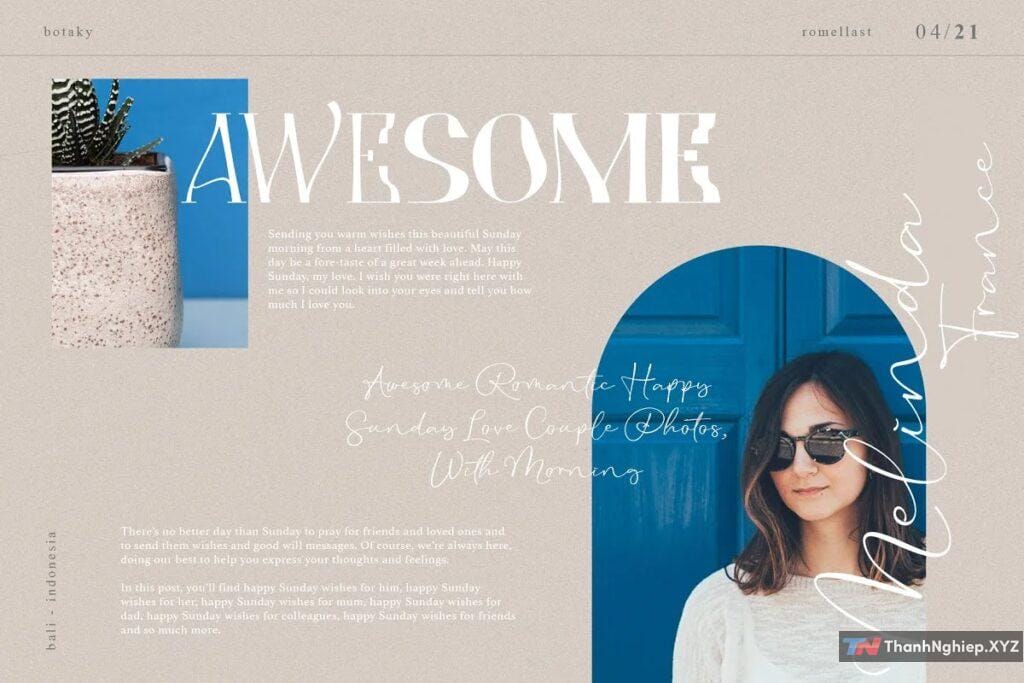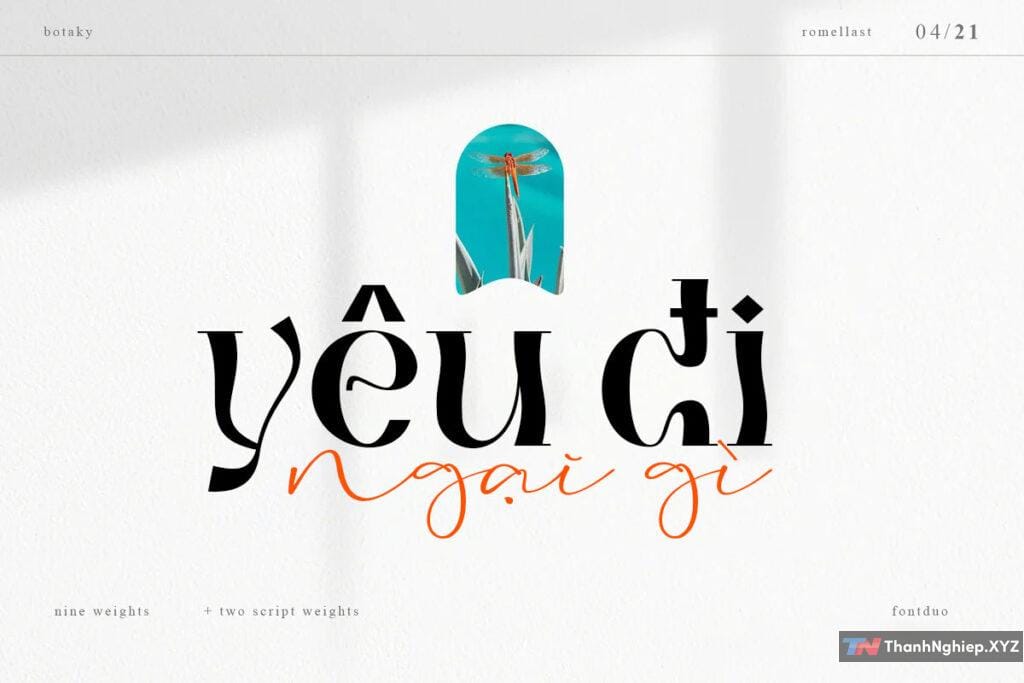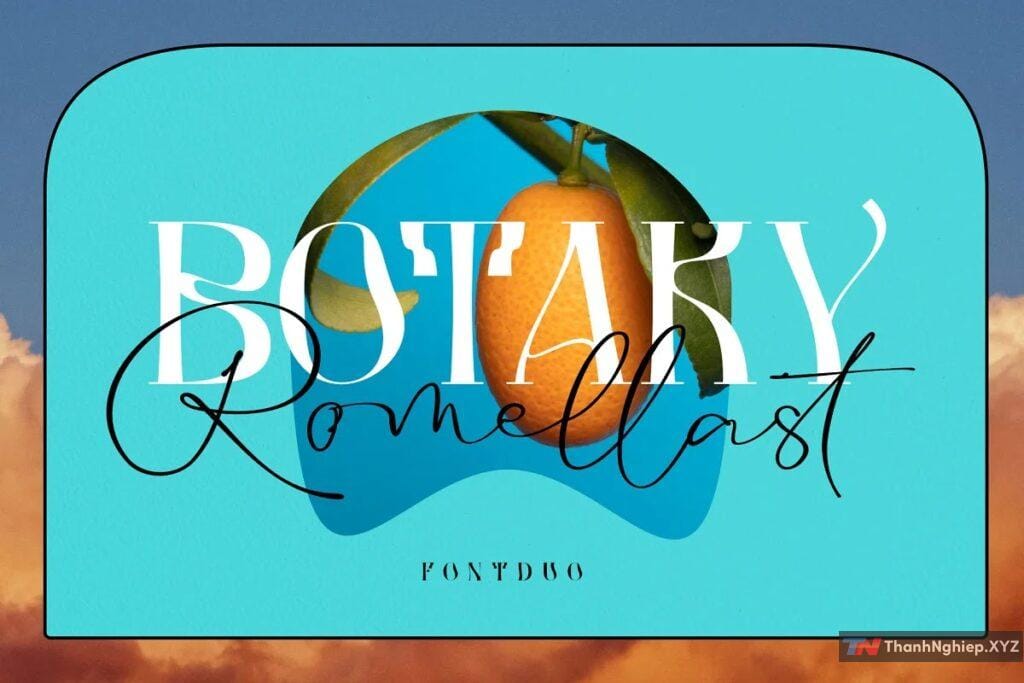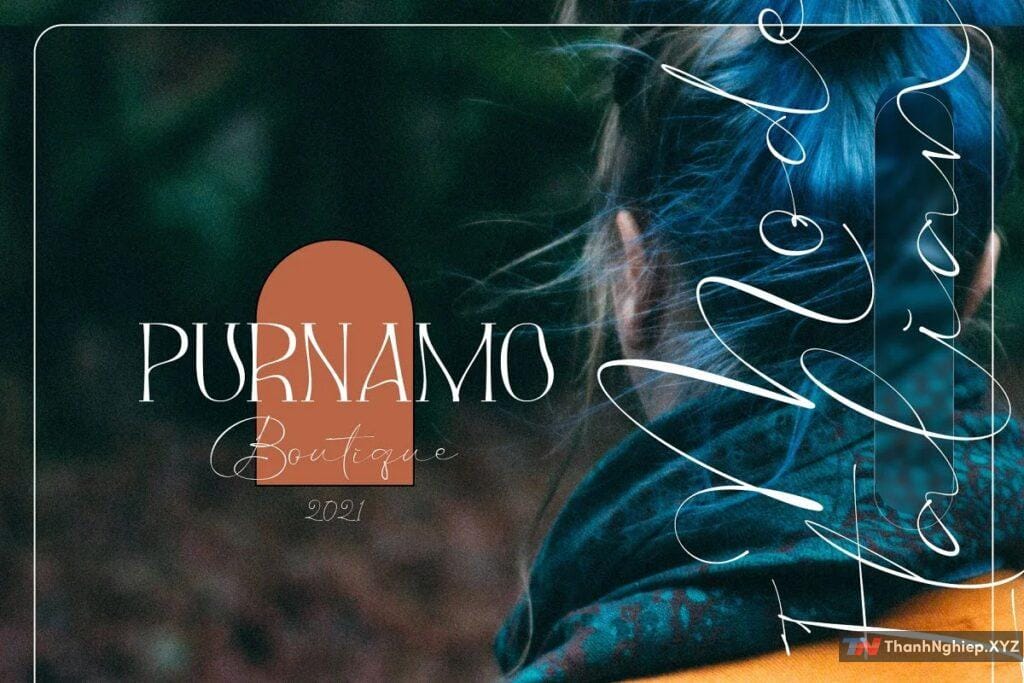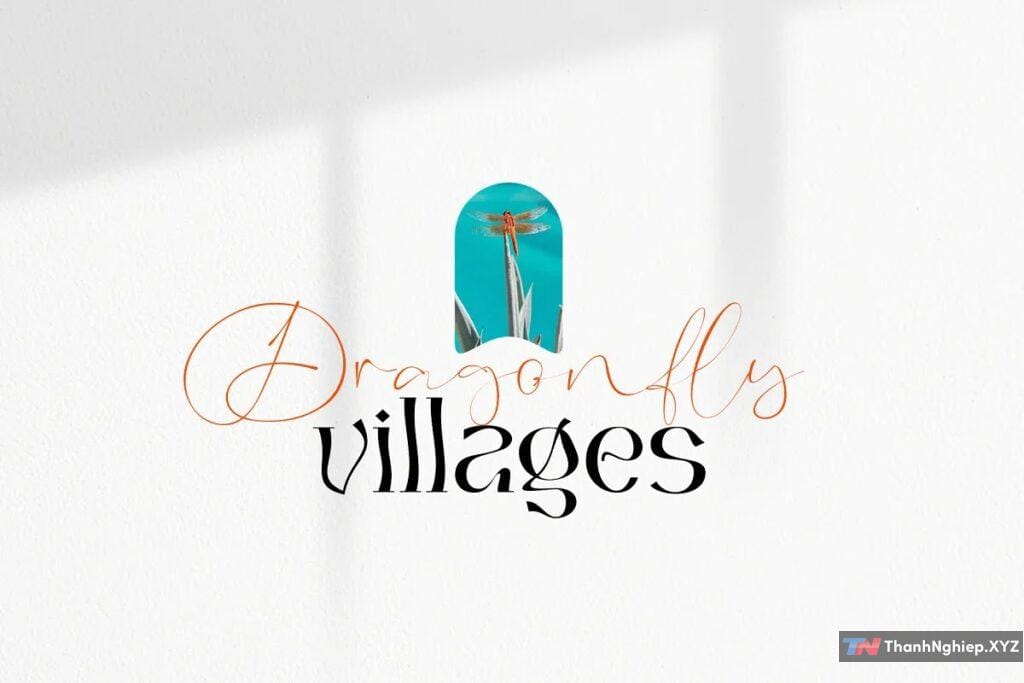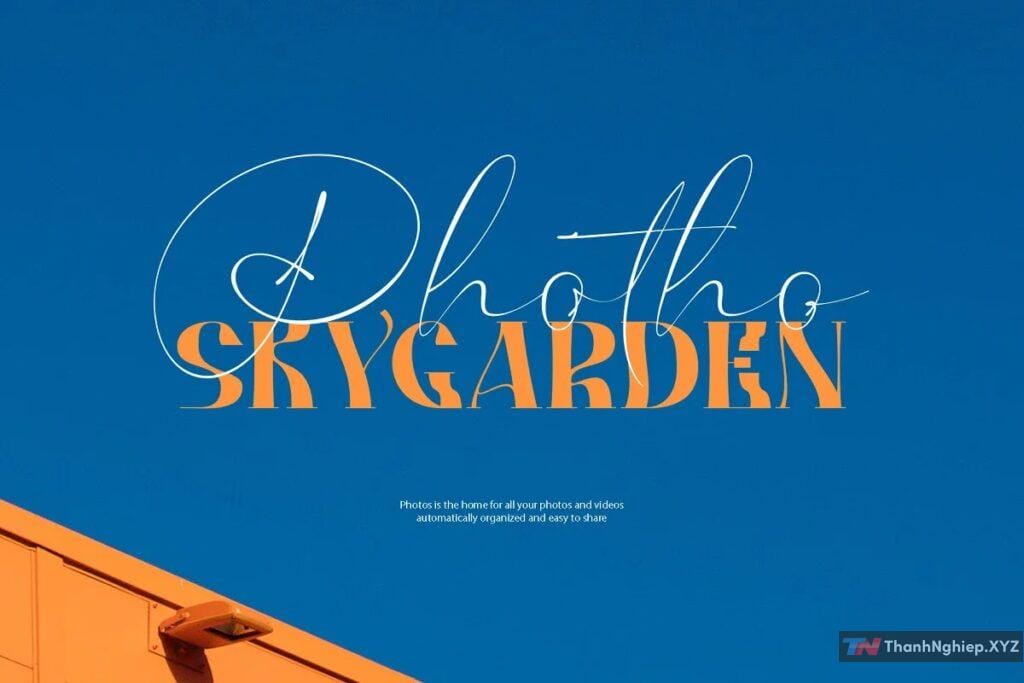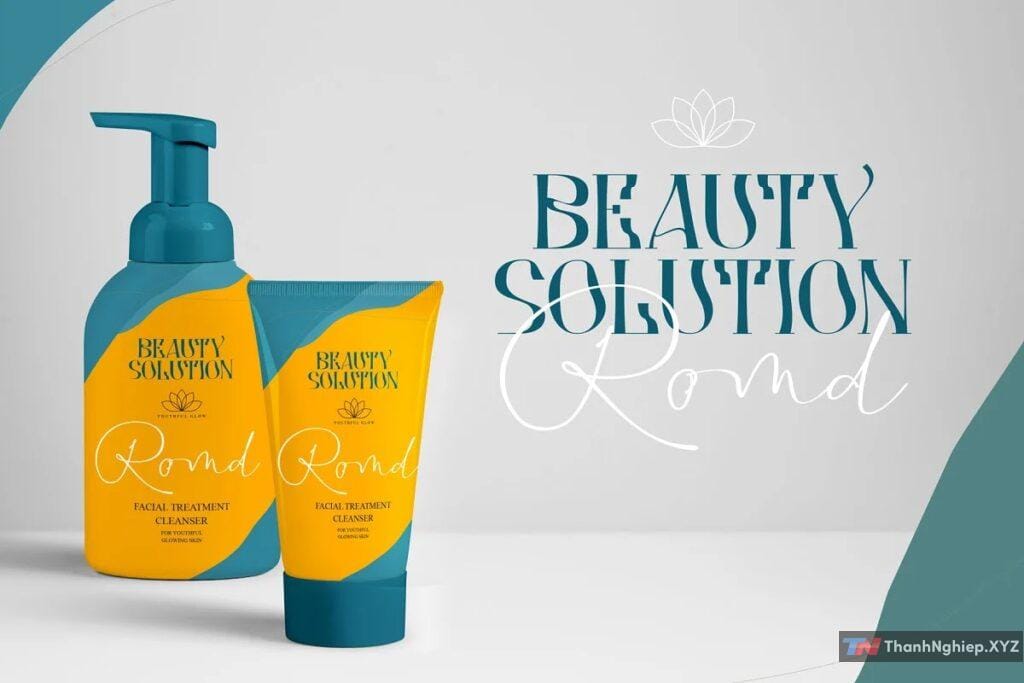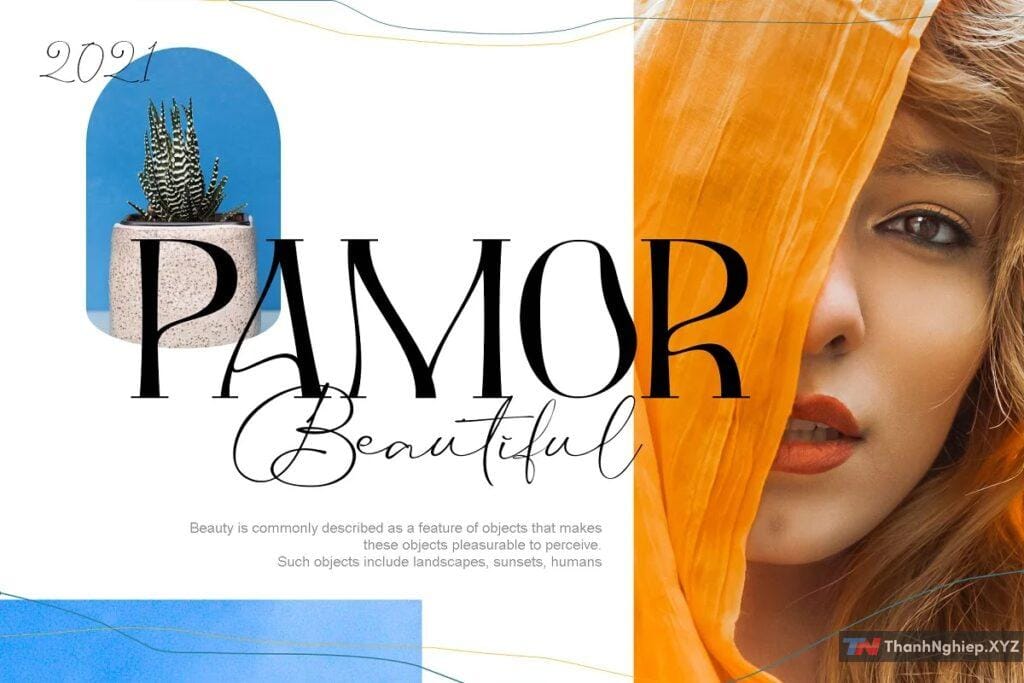
Giới thiệu Botaky Romellast font – Bộ đôi phông chữ độc đáo và tuyệt vời.
Bạn đang tìm kiếm một bộ font chữ vừa nghệ thuật, vừa mang đậm cá tính nhưng lại không quên sự mềm mại, thanh lịch? Hãy để Botaky Romellast Việt Hóa “chiếm spotlight” trong bộ sưu tập font của bạn! Với vẻ đẹp hòa quyện giữa nét cổ điển và hiện đại, đây là lựa chọn lý tưởng cho mọi dự án sáng tạo – từ thiết kế thiệp cưới đến logo thời thượng.
Botaky Romellast – Ngôi sao mới trong làng font chữ
Botaky Romellast không chỉ là một font chữ, mà là tác phẩm nghệ thuật sống động. Bộ sưu tập này bao gồm 10 font chữ khác nhau, được Việt hóa một cách hoàn hảo, giúp bạn tự do sáng tạo mọi kiểu thiết kế mà không cần lo lắng về dấu câu hay ký tự tiếng Việt.
Điểm nổi bật của font Botaky Romellast Việt Hóa
1. Phong cách độc đáo, thanh lịch
Mỗi font trong bộ Botaky Romellast đều có cá tính riêng. Đường nét chữ mềm mại, duyên dáng nhưng không thiếu sự phá cách, mang đến vẻ đẹp cân bằng giữa sự cổ điển và tính thời trang hiện đại.
2. Hỗ trợ tiếng Việt đầy đủ
Việt hóa chuẩn chỉnh từ A đến Z! Các dấu câu như “á”, “à”, “ẳ” đều được thiết kế tinh tế, giữ nguyên vẻ hài hòa với tổng thể font chữ.
3. Đa dạng kiểu dáng
10 font đi kèm trong bộ Botaky Romellast bao gồm:
- Regular: Đơn giản, gọn gàng nhưng vẫn cuốn hút.
- Italic: Thêm chút nghiêng để tăng phần lãng mạn, bay bổng.
- Bold: Đậm nét, mạnh mẽ, làm nổi bật tiêu đề hoặc logo.
- Và các phiên bản kết hợp phong cách cổ điển, hiện đại phù hợp với nhiều nhu cầu thiết kế.
4. Ứng dụng linh hoạt
- Thiết kế thiệp cưới, thư mời: Mang đến cảm giác lãng mạn, quý phái.
- Logo và nhận diện thương hiệu: Giúp thương hiệu của bạn toát lên sự chuyên nghiệp và sang trọng.
- Poster, banner quảng cáo: Thu hút ánh nhìn ngay từ cái nhìn đầu tiên với sự nổi bật của Botaky Romellast.
- Typography nghệ thuật: Làm đẹp cho các câu trích dẫn hoặc tiêu đề đầy cảm xúc.
5. Giao diện thân thiện, dễ sử dụng
Điểm khác biệt của 10 font Botaky Romellast Việt Hóa
- Thiết kế thủ công, chăm chút từng chi tiết: Không chỉ là một bộ font chữ, mà là sản phẩm của sự sáng tạo và tình yêu dành cho nghệ thuật chữ viết.
- Hài hòa giữa cổ điển và hiện đại: Đây không phải là một bộ font thông thường – Botaky Romellast mang đến vẻ đẹp phù hợp với mọi bối cảnh, từ sang trọng, thanh lịch đến cá tính, phá cách.
- Việt hóa đỉnh cao: Hãy quên đi nỗi lo font chữ bị lỗi dấu hoặc mất thẩm mỹ. Botaky Romellast Việt Hóa được tối ưu hóa để hoàn hảo với mọi văn bản tiếng Việt.
Tại sao nên sở hữu font Botaky Romellast Việt Hóa?
- Thăng hoa cảm xúc trong thiết kế: Botaky Romellast không chỉ giúp bạn hoàn thành dự án mà còn thổi hồn vào từng sản phẩm của bạn.
- Đa năng và linh hoạt: Dù bạn làm thiết kế cá nhân hay dự án chuyên nghiệp, bộ font này đều “cân” được tất.
- Nâng tầm thương hiệu: Sử dụng Botaky Romellast giúp logo, poster hay sản phẩm của bạn trở nên khác biệt và đáng nhớ.
Font chữ dành cho mọi nhà sáng tạo
10 font Botaky Romellast Việt Hóa không chỉ là một bộ font chữ mà là một công cụ nghệ thuật giúp bạn biến ý tưởng thành hiện thực. Từ những nét chữ mảnh mai như làn gió xuân đến những đường nét mạnh mẽ, đầy cá tính, bộ font này chắc chắn sẽ là người bạn đồng hành tuyệt vời trong mọi dự án sáng tạo.
Hãy thử ngay và khám phá thế giới thiết kế đầy cảm hứng mà Botaky Romellast mang lại! ✨🎨
Kết hợp hai font chữ BOTAKY và Romellast sẽ tạo ra một thiết kế quyến rũ, độc đáo, thanh lịch và hiện đại.
Hai font chữ này hỗ trợ đa ngôn ngữ và gõ được cả Tiếng Việt luôn nhé các bạn.